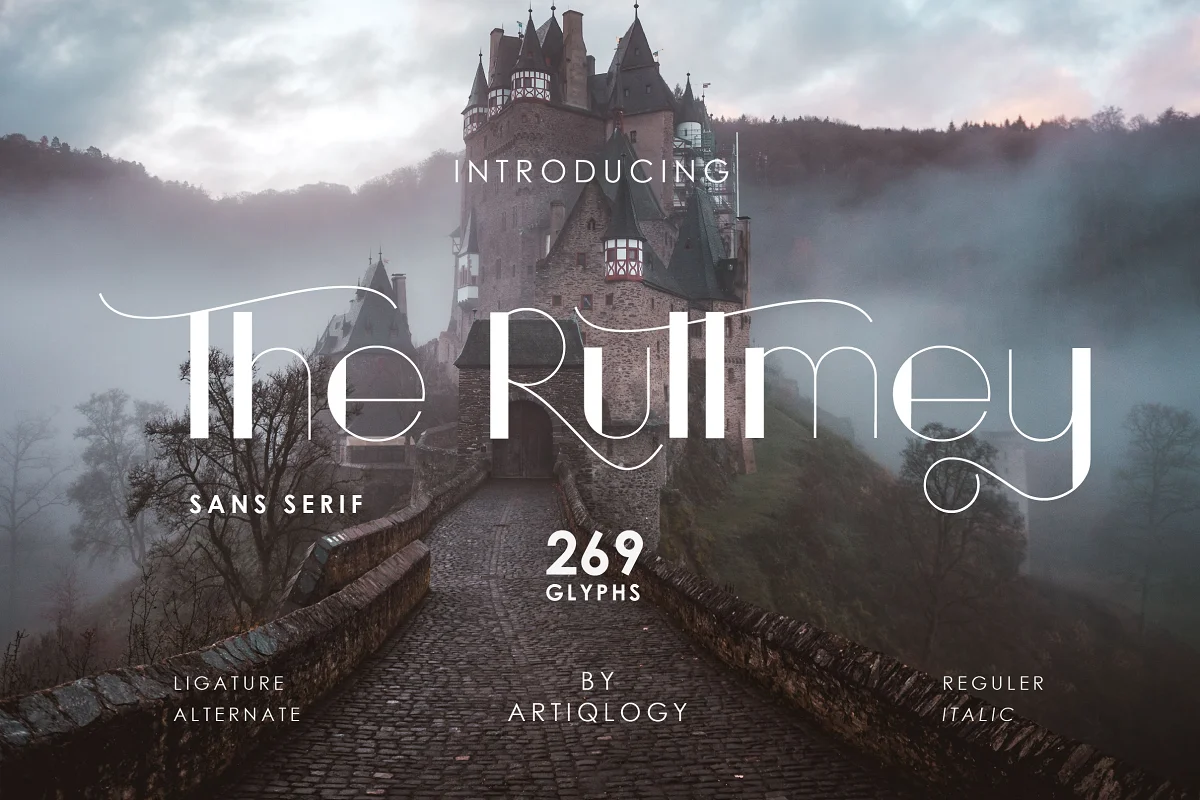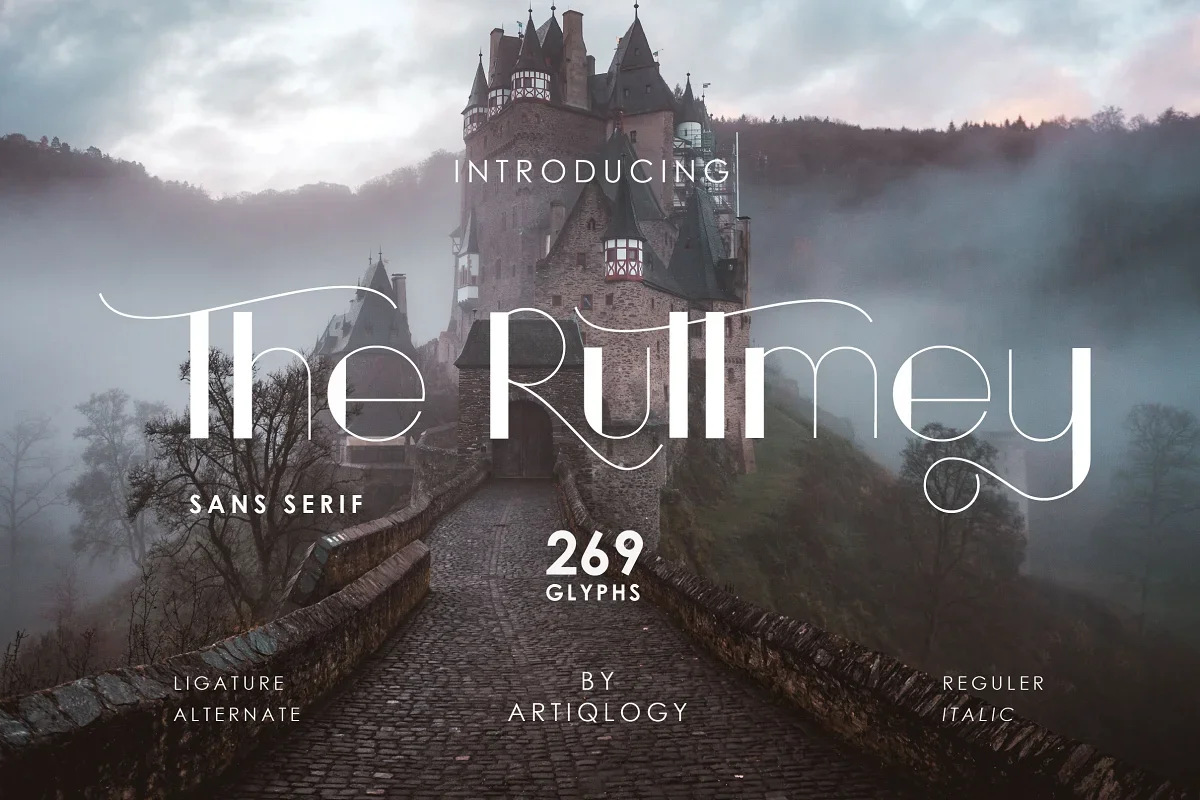
Название: The Ruttmey Font (2021)
Ruttmey - это элегантный и уникальный шрифт без засечек.
Благодаря аккуратному и красивому расположению букв этот шрифт будет отлично смотреться как в формальном, так и в неформальном дизайне.
Название: The Ruttmey Font (2021)
Ruttmey - это элегантный и уникальный шрифт без засечек.
Благодаря аккуратному и красивому расположению букв этот шрифт будет отлично смотреться как в формальном, так и в неформальном дизайне.